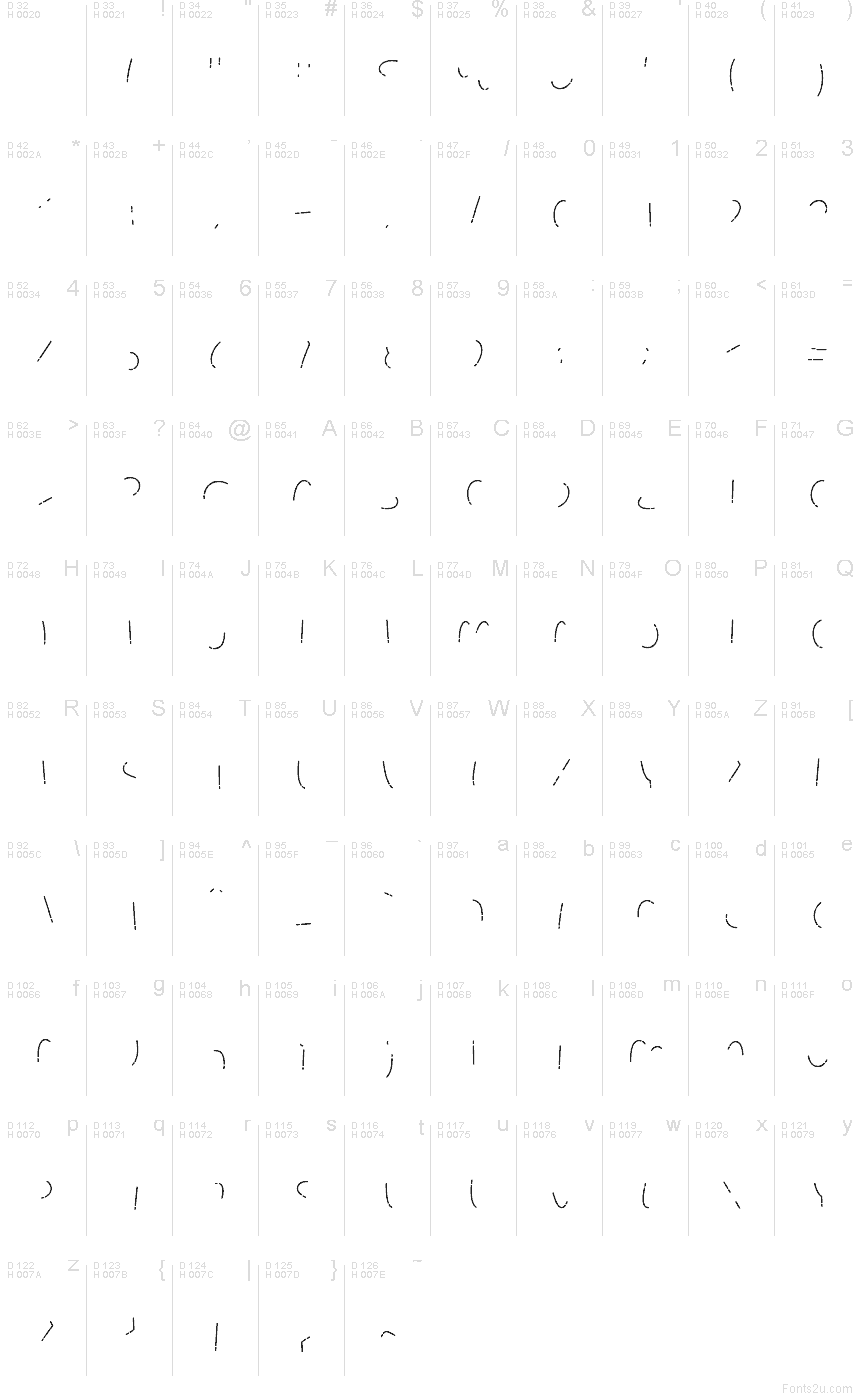
Rhuma Sinera Inline od Mabhal Studio je bezplatné, ručne kreslené písmo v komiksovom štýle s vysokými, tenkými znakmi a zámerne uvoľneným rytmom. Štíhle krivky, nerovnomerné oblúky a občasné oddelené ťahy dodávajú písmu rýchly, hravý dojem improvizovanej skice.
Toto bezplatné písmo sa hodí na detské plagáty, komiksové titulky, hravé obaly, nálepky, grafiku na sociálne siete či animované titulné karty. Vďaka riedkym ťahom a excentrickým tvarom vynikne najmä v krátkych nápisoch, kde si nepravidelná štruktúra zachováva svoj šarm bez toho, aby pôsobila preplnene.
Prezentácia a vizuálna ukážka písma Rhuma Sinera Inline
Mapa znakov písma Rhuma Sinera Inline
Mapa znakov písma Rhuma Sinera Inline: Základná latinka, strana 1
Glyfy písma Rhuma Sinera Inline — Základná latinka, strana 1